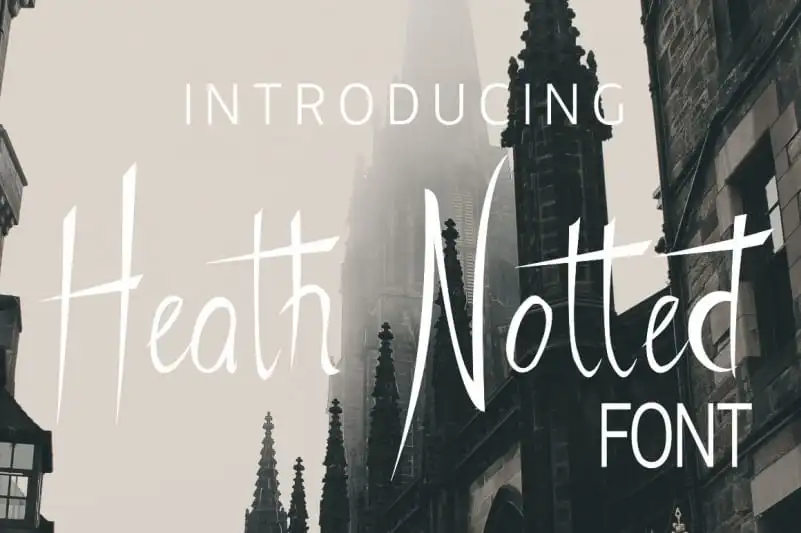
Heath Notted Script Font – Download Grátis
A Heath Notted Script Font é uma delícia para quem quer dar um toque especial ao seu design impresso ou digital. Inspirada na elegância misteriosa do Halloween, ela combina uma escrita noturna com um tom arredondado que faz dela uma escolha perfeita para qualquer projeto gráfico, especialmente aqueles que exigem um estilo distintivo e criativo. Seja para uma campanha publicitária de festas ou até mesmo para criar um design personalizado de Natal, esta fonte traz a essência das esquinas e das sombras em sua composição única. Sua riqueza e delicadeza tornam-a perfeita para criar um impacto visual poderoso e memorável. Foi criada para quebrar padrões convencionais, oferecendo uma forma noturna de escrita que se encaixa perfeitamente nos temas de Halloween ou temáticas sobrenaturais. Seja um anúncio em jornal, cartaz publicitário ou até mesmo em uma criação digital do seu site, a Heath Notted Script font trará vida e energia para qualquer projeto. Não apenas é uma fonte que se destaca em uma categoria de fonts gothis, mas também oferece um toque único à sua marca.